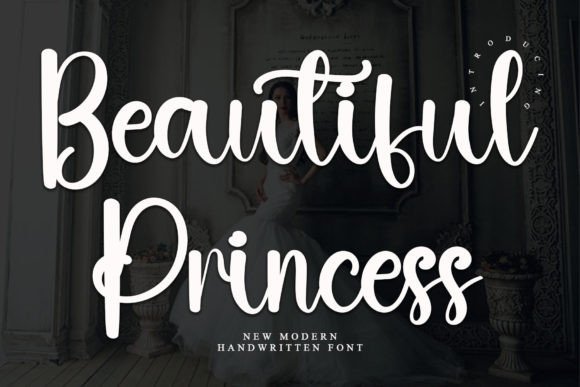
Beautiful Princess
Beautiful Princessのような高品質の素材をお探しの場合、このプレミアムパッケージはクリエイティブなプロジェクトに素晴らしい選択です。
精密に作られたBeautiful Princessは、クリーンなベクター、滑らかなタイポグラフィ、そして安心のための商用ライセンスを提供します。
POD(オンデマンド印刷)製品、結婚式の招待状、またはソーシャルメディアのグラフィックを作成している場合でも、Beautiful Princessは理想的です。